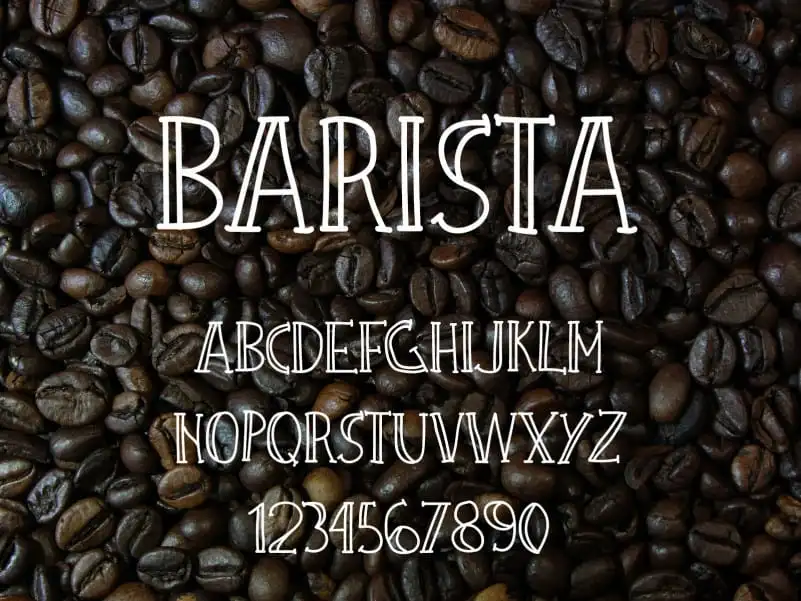
Barista Urban Coffee Display Font – Download Grátis
A Barista Urban Coffee Display Font é uma fonte de estilo urbano perfeita para estilos decorativos e visuais criativos. Perfeito para aplicação em capas de revistas, logotipos, mensagens e menus, essa fonte ilumina seu design com sua personalidade vibrante. Seja você um designer de moda ou um chef, uma vez que encontrou a Barista Urban Coffee Display Font, vai perceber que os limites para o seu trabalho são apenas limitados pela sua imaginação. Este estilo de fonte urbanizado e contemporâneo traz a sensação dos cafés da cidade mais movimentada diretamente para suas criações, criando um visual único que certamente deixará sua marca. Seja para uma nova campanha publicitária ou apenas decorar o menu de um restaurante, essa fonte promete uma experiência memorável e única.